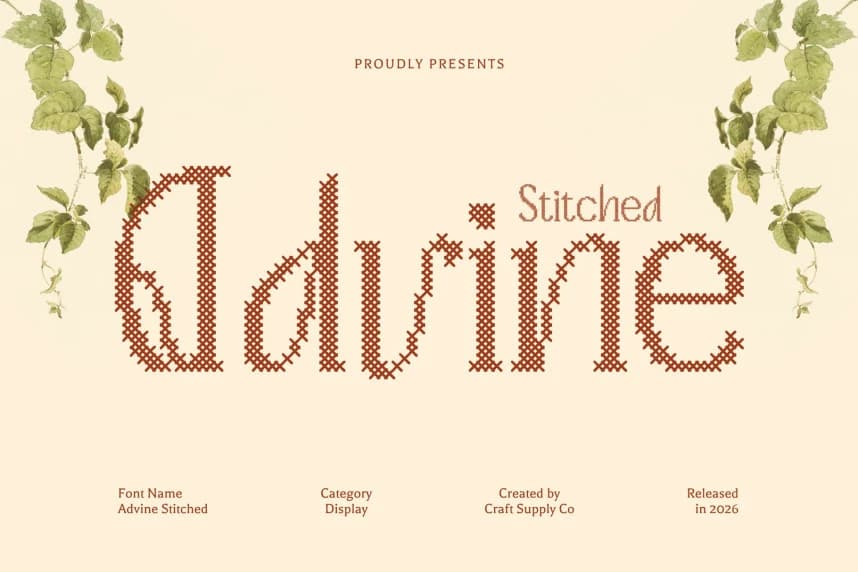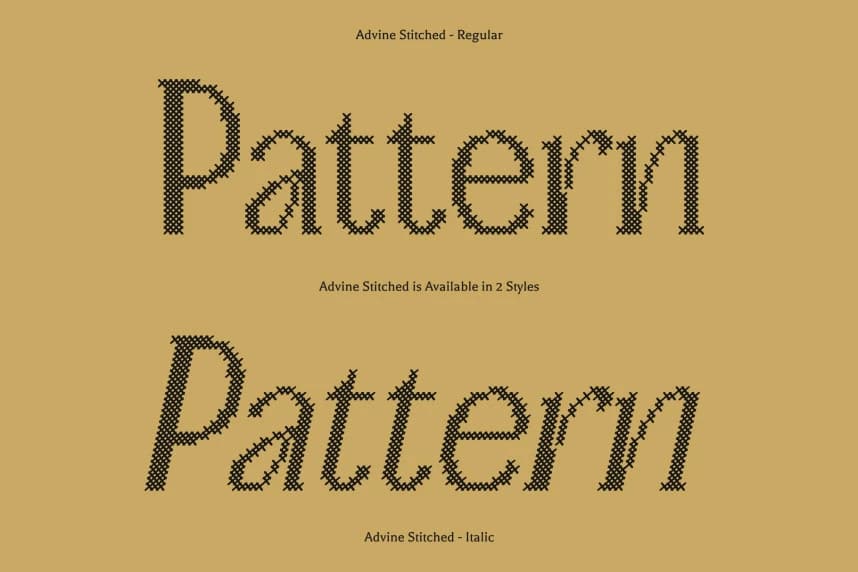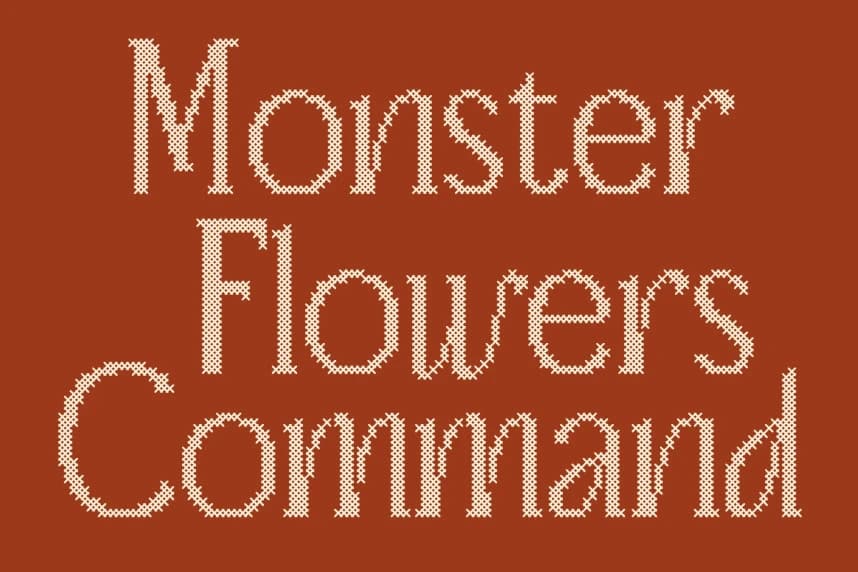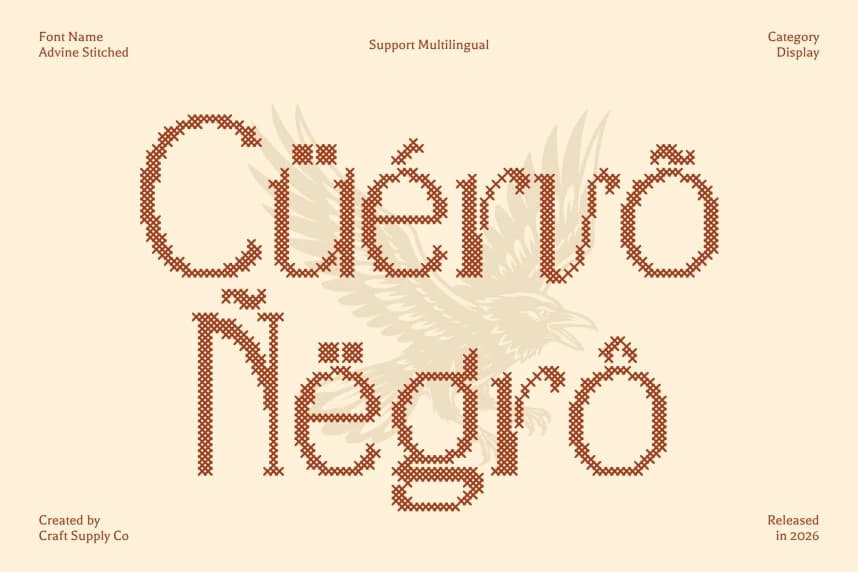
Advine Stitched Font
Advine Stitched Font – Art Nouveau ilhamını el yapımı sıcaklıkla kucaklayan, zamansız zarafete sahip düşük kontrastlı bir serif fontudur. Bu rafine düşük kontrastlı serif fontu, çizgi kalınlıklarındaki ince varyasyonlarla okunabilirliği artırırken zarif, klasik bir görünüm sağlar.
Advine Stitched Font – Art Nouveau ilhamını el yapımı sıcaklıkla kucaklayan, zamansız zarafete sahip düşük kontrastlı bir serif. Bu, çizgi kalınlığındaki ince varyasyonlar tarafından karakterize edilen, okunabilirliği artıran ve zarif, klasik bir görünümü koruyan rafine bir düşük kontrastlı serif yazı tipidir.